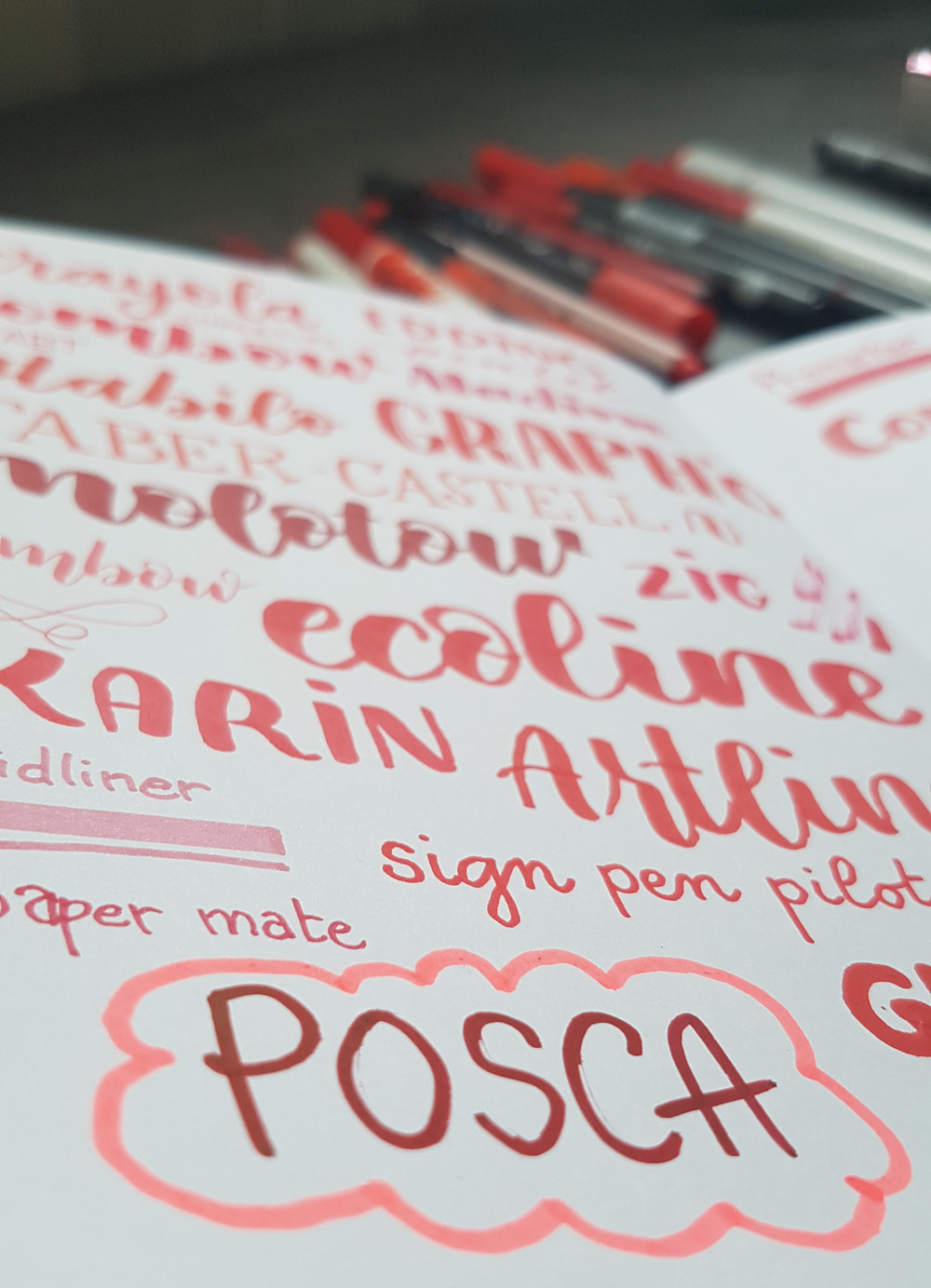
MAÎTRISER L'ART DU BRUSH LETTERING
Découvre comment tracer de belles lettres au feutre pinceau
J’entends souvent les gens dire qu’ils ne sont pas des artistes ou qu’ils ne sont pas doués en dessin par exemple
Pourtant, retrouver le plaisir de dessiner comme lorsqu’on était enfant est à la portée de tout le monde.
Découvrez le lettering,  l’art de dessiner les lettres, c’est une forme moderne et libre de calligraphie.
Maîtriser l'art du Brush Lettering
Apprenez l'art du Lettering à travers le brush
Ce que tu vas découvrir :
• La posture et les gestes de bases pour ne pas prendre de mauvaise habitude
• Les différents outils à utiliser pour donner vie à de sublimes lettres
• Comment tracer un alphabet complet en minuscule et majuscule
Le Lettering, ça donne envie. Pouvoir être fier de ses réalisations et les poster sur les réseaux sociaux. Pouvoir vendre ces réalisations pour des anniversaires ou encore des mariages...
Mais après s'être renseigné sur le sujet, on se rend compte rapidement que ce n'est pas si facile de débuter :
• Par où commencer ? Quelle type de phrase ? Quel style ?
• Le syndrome de la page blanche
• J'ai beau recopier un modèle, le résultat n'est vraiment pas concluant
Tu t'es déjà intéressé(e) au Lettering mais:
• Tu as fait défiler pendant des heures les sublimes images sur Instagram ou Pinterest mais cela te décourage au lieu de t’inciter à passer à l’action.
• Tu as acheté quelques feutres et livres ou magazines sur le sujet mais tu as renoncé au bout de quelques essais et ils sont restés au fond du placard. Trop difficile, pas le temps !
• Au moment où tu te décides à te mettre au lettering, d’autres priorités arrivent constamment : boulot, repas à préparer ou juste flemme (« tiens, y’a quoi sur Netflix ce soir?»).
Pourtant, il est réellement possible de pouvoir devenir un(e) réel(lle) pro du Lettering !
À mes débuts, je me demandais vraiment si j'y arriverais un jour. Mais j'ai persévéré et j'ai passé des heures à décortiquer mes difficultés.
J'en ai ainsi conclu que ce n'était pas de ta faute si tu n'y arrivais pas. Toutes ces vidéos, ces tutos qui font des démonstrations sont souvent en accéléré et, par ailleurs, ne t'enseigne pas comment comprendre, comment te corriger par toi-même. Tu ne sais pas pourquoi tu fais toujours les mêmes erreurs sur tel ou tel trait.
En vérité, pas besoin de talent particulier, ce n'est pas inné. Il suffit de connaître quelque astuces, de les appliquer correctement, de suivre un bon ordre d'apprentissage.
Cela permet de prendre de bonnes habitudes dès le départ et de finalement réussir en très peu de temps. J'aime comparer cela aux gammes d'un musicien sauf qu'il n'y a pas besoin d'années de pratique laborieuse ni d'apprendre tout un solfège compliqué et rébarbatif.
Tu as envie :
• De t'amuser dans la créativité
• De découvrir des techniques inédites de Brush Lettering  pour donner vie à ton imaginaire
• Reprendre confiance en soi et en ta capacité à créer.
• Utiliser tes nouvelles capacités pour créer des cartes, affiches, illustrations
Alors ça te parle ?
J'ai une méthode pour progresser en seulement quelques semaines, même si tu es complètement débutant(e). Si tu as déjà essayé, mais sans succès, tu es aussi au bon endroit ! Et si tu pratiques déjà un peu, tu apprendras de nouvelles astuces pour un résultat toujours sublime.
Avec ma méthode, tu t’épargnes des jours, des semaines, des mois de recherches Internet et de frustration à tenter en vain de maîtriser ce maudit feutre pinceau, de comprendre comment former de belles lettres, créer de sublimes compositions dont tu seras fièr(e). Le Lettering aquarelle n’aura plus aucun secret pour toi. Mes meilleures astuces te seront également révélées, fruits d’un long travail d’analyse et de comparaison du travail de différents artistes.
Mais si tout est clair dans ton esprit et tu te sens prêt(e) à découvrir la magie du Brush Lettering ?